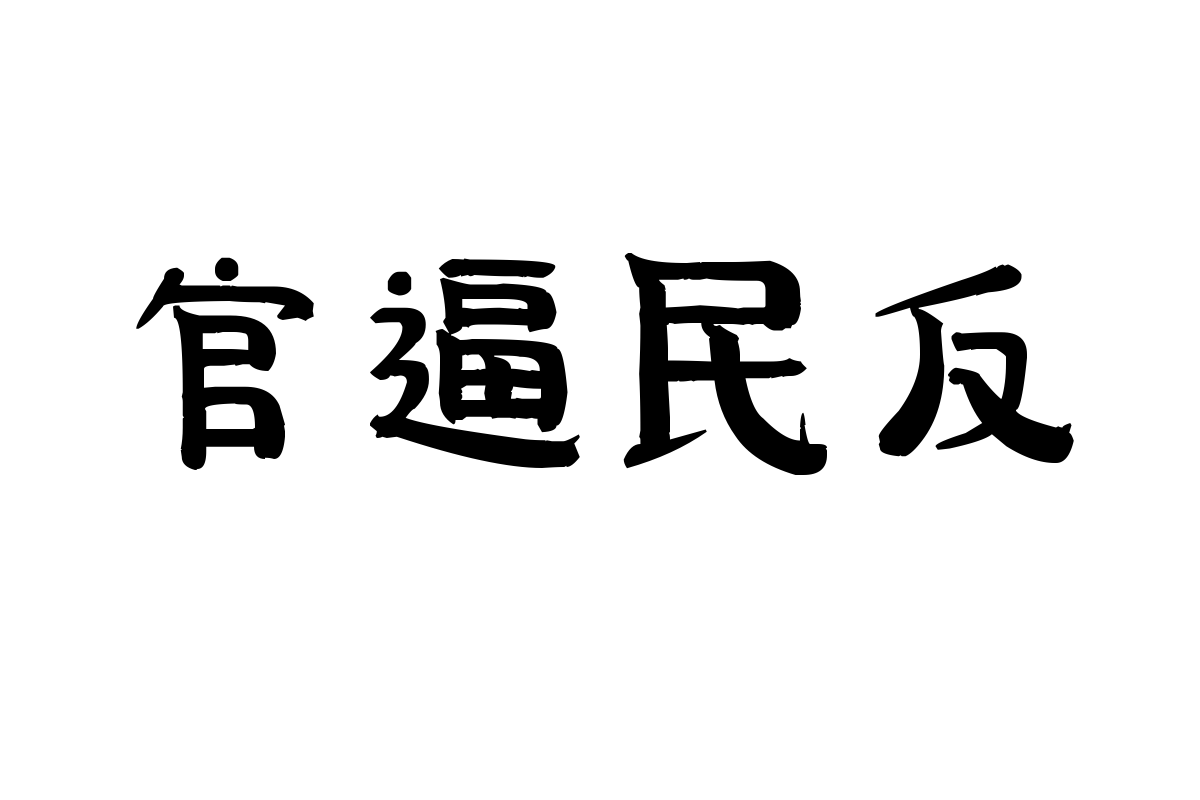
仓耳孔璐楷书字体是一种独特的书法字体,它结合了楷书的规范性与仓耳孔的古朴感,形成了一种既有力度又有美感的字体风格。
仓耳孔是中国古代的一种文字符号,它的笔画粗细不一,给人一种古朴的感觉。而楷书则是汉字书写的一种规范形式,它的笔画清晰、结构严谨,给人一种整齐的感觉。
仓耳孔孔璐楷书字体将这两种风格结合在一起,使得字体既有楷书的规范性,又有仓耳孔的古朴感,既有力度又有美感。这种字体非常适合用于书法创作,也很适合用于设计领域,因为它既有古典的韵味,又有现代的气息。